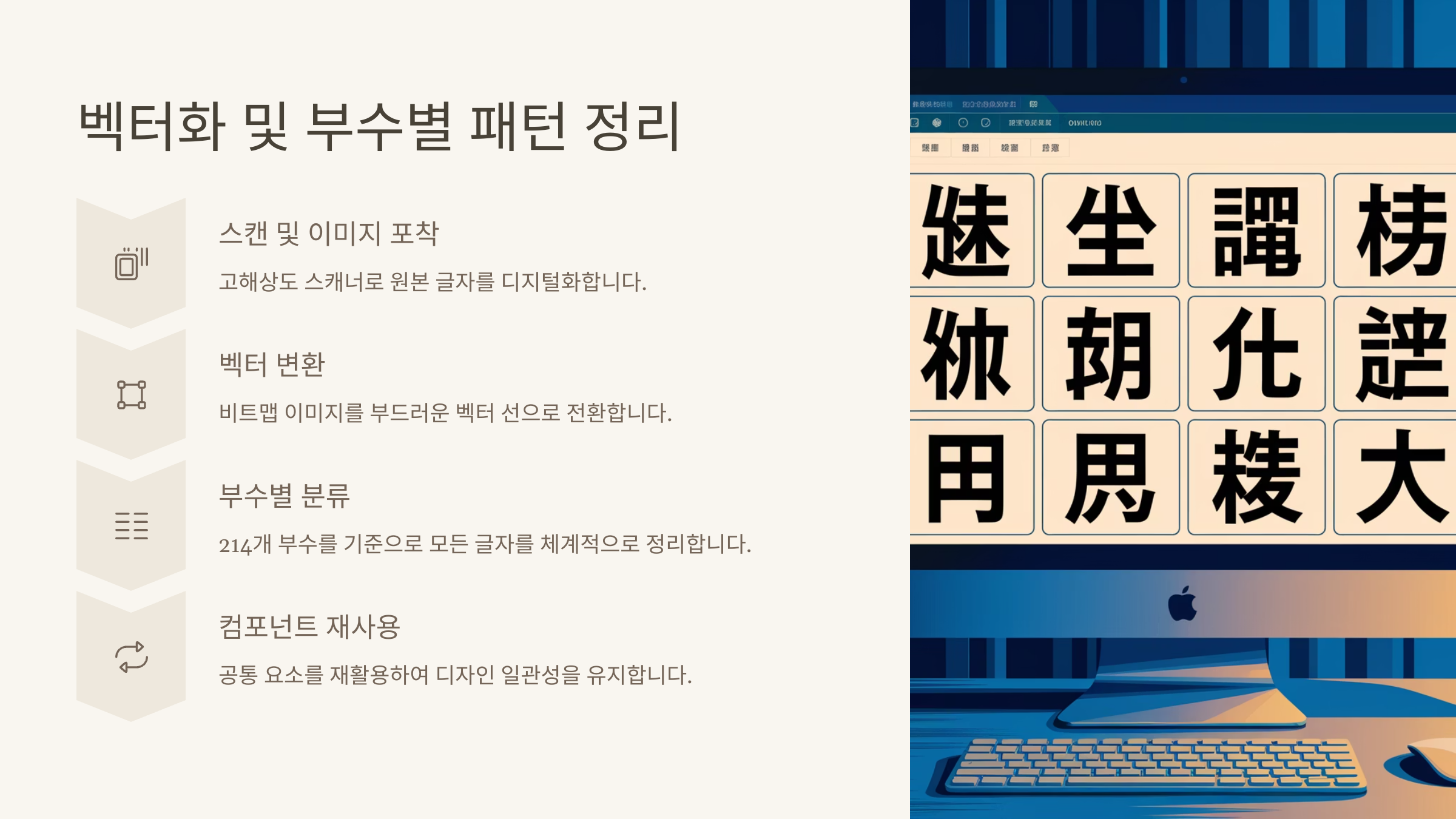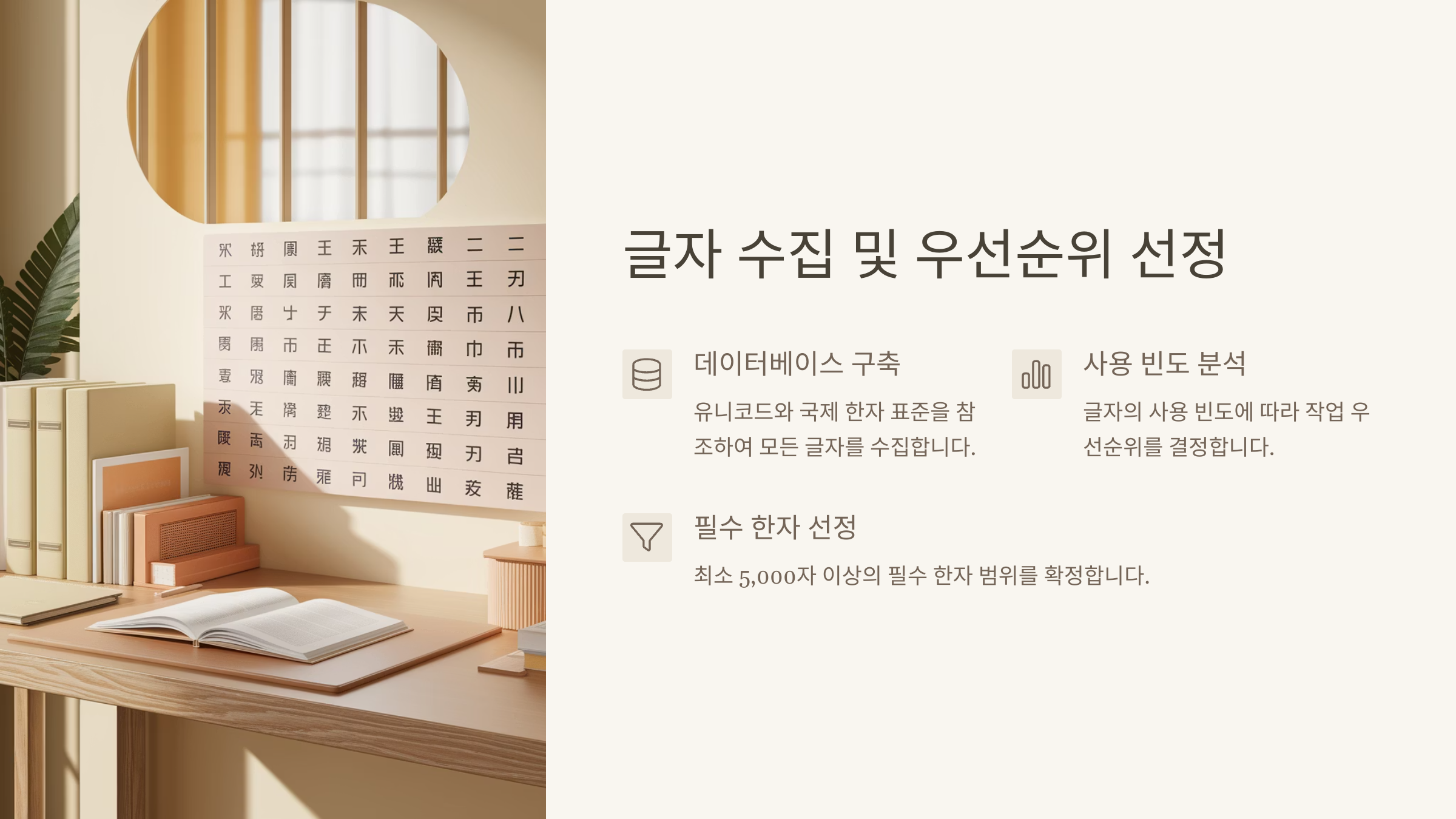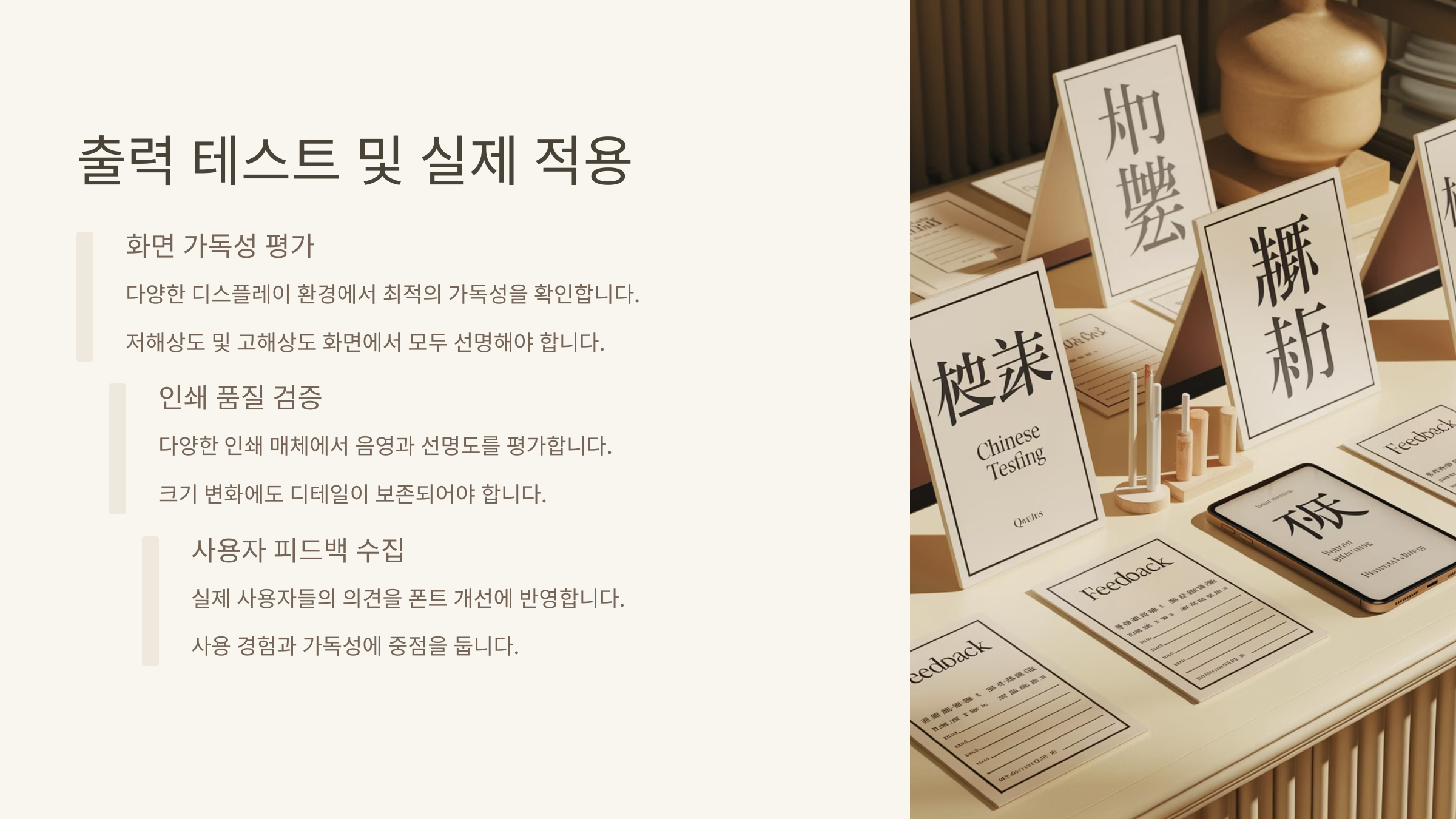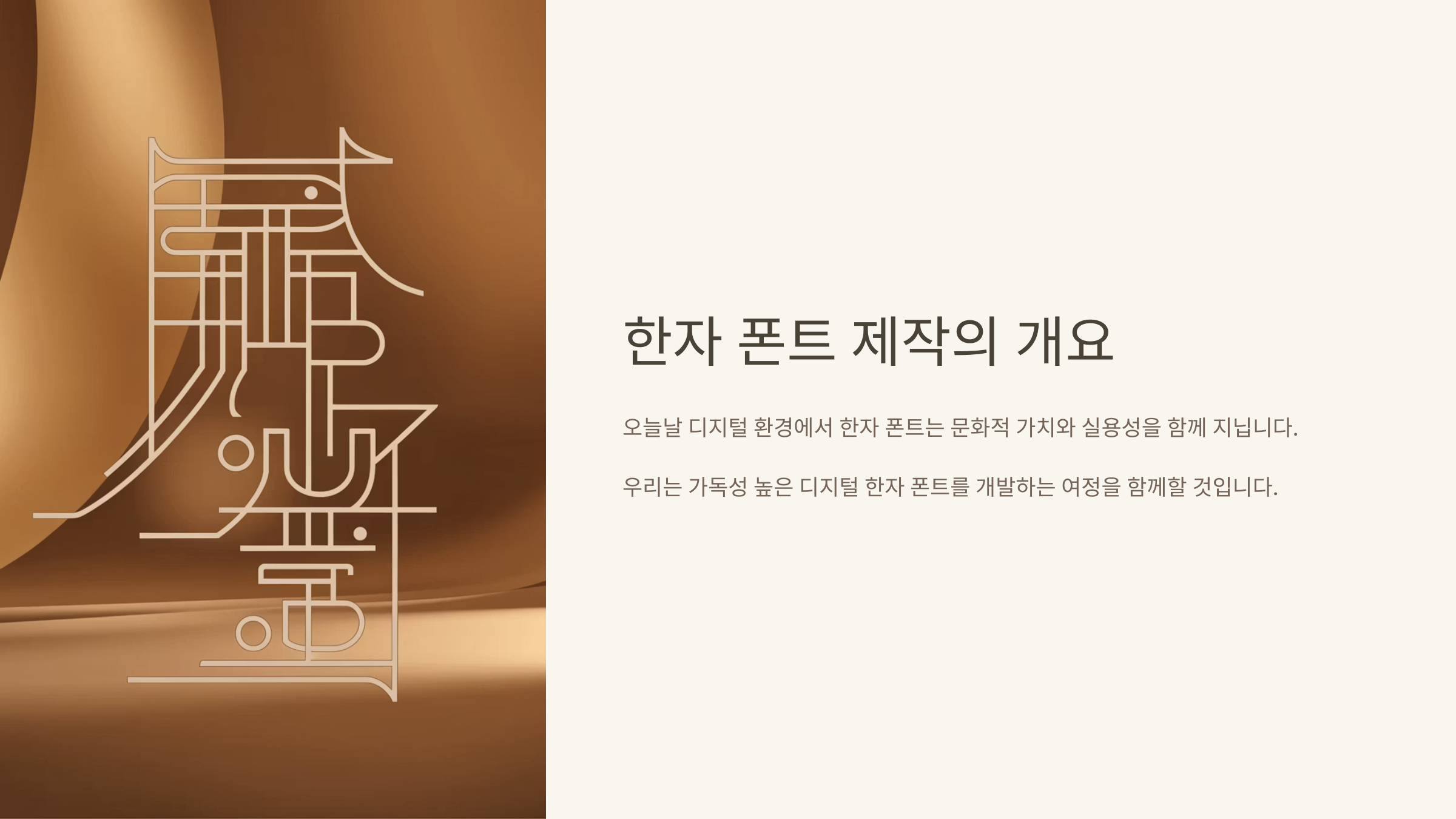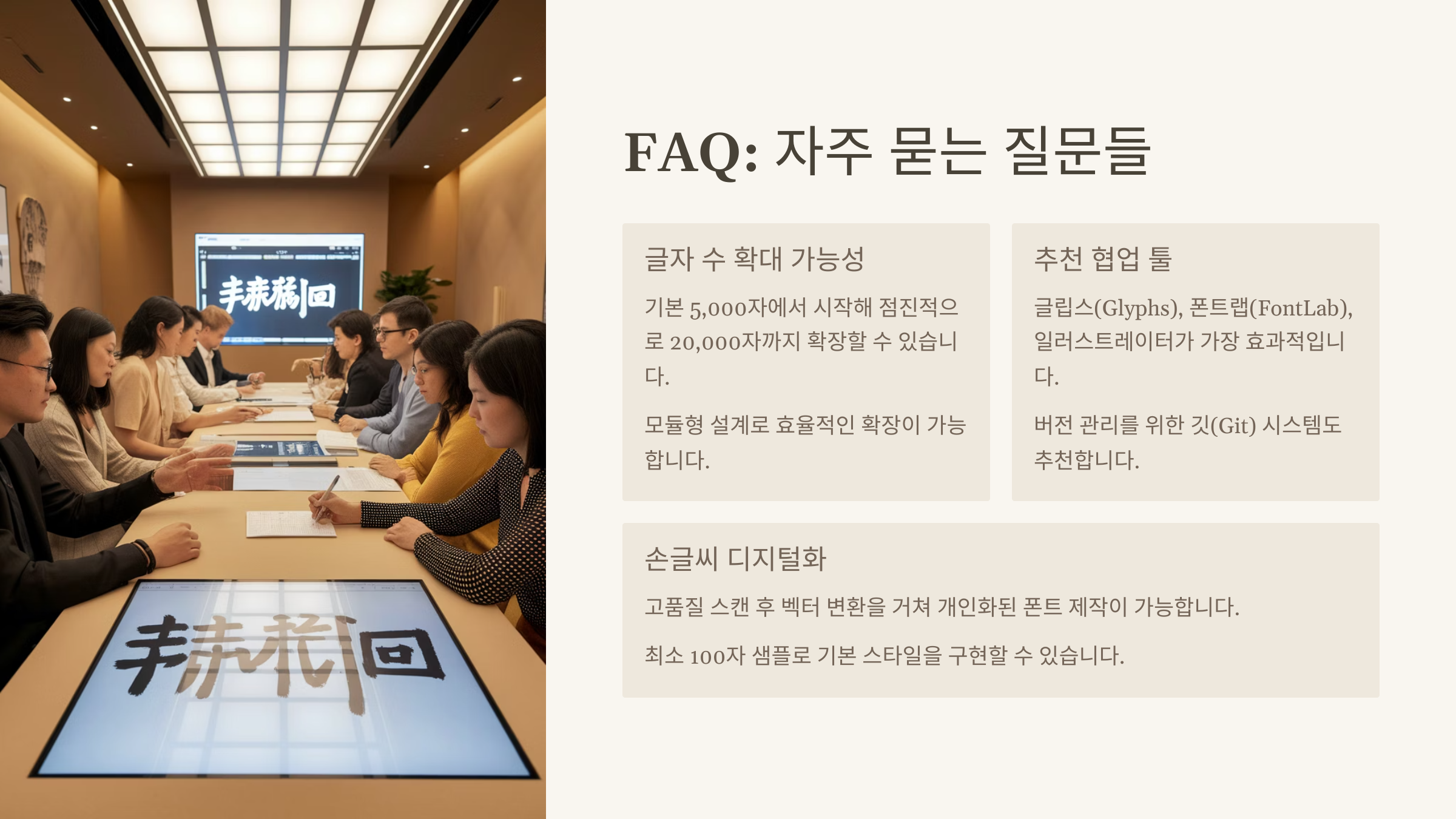
한자 폰트 제작은 일반 한글이나 영문 폰트보다 훨씬 복잡하고 방대한 작업이에요. 왜냐하면 한자는 수천 개의 글자를 포함하고 있고, 각 글자의 구조도 다양하기 때문이에요. 그만큼 완성했을 때의 성취감도 크답니다! 🀄
한자 폰트는 전통적인 서예에서 영감을 받은 디자인부터 현대적인 모노라인 스타일까지 다양하게 활용돼요. 특히 전통 행사나 동양적인 콘텐츠 디자인에서는 독창적인 한자 폰트가 큰 차별화 요소가 되기도 하죠.
지금부터는 한자 폰트를 직접 만드는 데 필요한 준비 과정부터 드로잉, 벡터화, 자동 조합, 테스트까지 모든 절차를 하나하나 소개해줄게요. 시작해볼까요? 😊
📘 한자 폰트 제작의 개요와 특징
한자 폰트는 기존의 알파벳이나 한글 폰트보다 훨씬 많은 글립을 요구해요. 기본적으로 중국어 간체자는 3,500자 이상, 번체자는 5,000자 이상이 필요하죠. 한국에서 사용되는 한자는 교육용 1,800자 외에도 인명, 고사성어 등에서 4,000자 이상이 쓰여요.
한자의 가장 큰 특징은 부수(部首)와 획의 조합이에요. 그래서 글자 전체를 하나씩 새로 그리기보단, 부수와 주요 구성 요소를 재활용할 수 있는 구조를 설계하는 게 핵심이에요. 이 부분이 자동화 가능한 구조 설계와 직결돼요.
한자 폰트를 만들기 위해서는 먼저 내가 만들고자 하는 범위를 정하는 게 중요해요. 전체 8천 자를 다 만드는 건 비현실적일 수 있으니, 1차로 300자, 2차로 1,000자 이런 식으로 범위를 나누는 게 효율적이에요.
또한 폰트의 용도도 정해야 해요. 웹용인지, 인쇄용인지, 로고 타입인지에 따라 선의 굵기나 정밀도가 달라져야 하거든요. 서예 느낌의 획감을 살릴지, 미니멀한 디지털 느낌으로 갈지도 처음부터 명확히 정해야 효율적인 제작이 가능해요. 🖌️
🈶 한자 폰트와 한글/영문 폰트 비교
항목 한자 폰트 한글/영문 폰트
필요 글자 수 3,000~10,000자 한글 2,350자 / 영문 100자
글자 구성 부수 + 파생부 + 결합 기본자 직접 제작
제작 방식 자동 조합 활용 필수 글립별 수동 제작 가능
내가 생각했을 때, 한자 폰트는 양적인 도전뿐만 아니라 구조적인 설계의 예술이에요. 드로잉 감각과 함께 데이터적 사고까지 요구되기 때문에 폰트를 진지하게 만들어보고 싶은 사람에게는 최고의 프로젝트라고 느껴져요. 🤓
📚 글자 수집과 우선순위 선정
한자 폰트 제작에서 가장 먼저 해야 할 일은 어떤 글자를 만들 것인지 정리하는 작업이에요. 한자 수는 무려 7만 자 이상이지만, 실생활에서 자주 쓰이는 글자는 그중 일부에 불과하거든요. 그래서 우선순위를 똑똑하게 정리하는 게 효율을 크게 높여줘요. 🧠
가장 기본이 되는 건 교육용 상용한자(1,800자)예요. 한국 교육과정에서 배울 수 있는 글자들이고, 일상적인 문서나 책에서도 가장 많이 쓰이는 글자들이에요. 국립국어원이나 한자능력시험 공식 웹사이트에서 리스트를 쉽게 찾을 수 있어요.
다음으로는 성씨와 이름에 자주 쓰이는 인명용 한자(약 5,000자)가 있어요. 디자인 명함, 족보, 졸업증명서 등 다양한 인쇄물에 활용되기 때문에 상용한자 다음으로 높은 우선순위예요. 이름에 자주 등장하는 글자는 폰트 가독성에서 특히 중요하답니다.
그리고 나서 고려할 수 있는 건 고사성어나 문장 구성에 자주 쓰이는 고빈도자(사용빈도 1,000위 이내 한자)예요. 뉴스, 논문, 고전 텍스트 등에서 반복적으로 등장하는 글자들을 데이터 기반으로 정리한 자료들도 있으니 참고하면 좋아요.
📖 한자 제작 우선순위 예시 리스트
우선순위 구성 추천 수량
1단계 상용한자 (교육용) 1,800자
2단계 인명용 한자 약 5,000자
3단계 고빈도/문장형 한자 약 500~2,000자
이렇게 정리된 우선순위에 따라 글자 목록을 엑셀이나 구글 스프레드시트로 관리해보면 좋아요. 어떤 글자가 완성됐는지, 어떤 글자는 부수가 겹치는지 추적할 수 있어서 제작 속도도 빨라지고 중복 작업도 줄어들어요. 📊
✍️ 한자의 구조와 드로잉 전략
한자는 하나의 글자가 곧 ‘작품’이에요. 단순한 획 몇 개로 이루어진 게 아니라, 부수와 파생부의 조합으로 복잡한 구조를 이뤄요. 그래서 드로잉을 할 때 가장 먼저 해야 할 일은 구성 분석이에요. 어떤 부분이 반복되고, 어디가 독립적인지를 파악하는 게 핵심이에요. 🔍
예를 들어, ‘語(말씀 어)’는 왼쪽에 言(말씀 언), 오른쪽에 吾(나 오)가 있어요. 이렇게 부수와 부수가 결합된 형태는 전체 드로잉을 다시 그리는 것보다 부분을 나눠서 조립하는 전략이 훨씬 효율적이에요.
그래서 보통 폰트 디자이너들은 자주 쓰이는 부수나 부속 요소를 따로 벡터로 만들어 두고, 이를 재조합해서 글자를 구성해요. 이렇게 하면 3천 자 이상을 만들 때 중복 작업을 줄일 수 있고, 스타일 일관성도 유지할 수 있어요.
획 순서와 균형도 중요해요. 한자는 획이 많기 때문에 전체 비율이 흐트러지기 쉬운데, 중심축과 획의 리듬을 고려해서 균형을 맞추는 게 핵심이에요. 너무 촘촘하게 그리면 인쇄나 웹에서 가독성이 떨어지고, 너무 벌어지면 품격이 떨어져 보여요. 🎨
🧩 한자 구성 요소 분석 예시
글자 좌우/상하 구성 부수 드로잉 팁
語 좌우형 言 言과 吾를 따로 제작 후 결합
學 상하형 子 ‘子’는 반복 사용, ‘冖’도 재활용
體 좌우형 骨 骨, 豆 등 부분별 드로잉 추천
한자의 드로잉은 시간이 오래 걸리지만, 부분을 잘게 쪼개서 모듈처럼 구성하면 효율이 엄청 올라가요. 게다가 나중에 다른 글자 제작에도 그대로 재활용 가능해서 작업 시간이 확 줄어요. 💡
🖱️ 벡터화 및 부수별 패턴 정리
드로잉이 끝났다면, 다음은 한자를 ‘벡터’ 형태로 정리하는 단계예요. 폰트 제작 도구에서 글립을 만들기 위해서는 모든 글자가 벡터 방식이어야 하거든요. 픽셀로 구성된 이미지는 확대하면 깨지지만, 벡터는 어떤 크기에서도 선명하게 유지돼요. ✨
일러스트레이터나 Glyphs, FontLab 같은 툴에서 펜 툴을 활용해 하나하나 선을 따주는 게 기본이에요. 이 작업은 처음엔 시간이 오래 걸리지만, 부수 단위로 만들어놓으면 반복해서 쓸 수 있어서 전체 글자 수가 많아질수록 효율이 급상승해요. 📈
이때 가장 중요한 게 ‘부수 패턴화*예요. 예를 들어 ‘氵(물 수)’ 부수는 여러 한자에서 같은 위치에 쓰이기 때문에 위치, 비율, 선의 곡률까지 동일하게 만들어야 전체 폰트에 통일성이 생겨요. 이런 부수별 템플릿을 만드는 걸 추천해요.
패턴화된 부수는 별도 레이어로 저장하거나, 라이브러리로 만들어 두면 이후 글립 조립할 때 쉽게 가져다 쓸 수 있어요. 특히 반복 부수(言, 木, 扌, 忄 등)는 반드시 템플릿화해서 재사용을 염두에 둬야 해요. 😎
🧱 대표 부수 패턴 정리 예시
부수 자주 사용되는 예 위치 벡터화 팁
氵 海, 洋, 湖 좌측 균형 맞춘 3획 반복 사용
言 語, 話, 記 좌측 글자폭 25% 내외로 고정
忄 情, 忍, 息 좌측 중앙축 기준 좌정렬
부수마다 고유 스타일을 정해두면, 새 글자 만들 때 고민할 게 확 줄어요. 처음에는 귀찮아 보여도, 부수 패턴화를 해두면 나중에 한자 1,000자를 만드는 데 드는 시간이 절반 이하로 줄 수 있어요. 효율의 핵심 포인트예요! 🚀
🔧 글립 조합과 자동 생성 기법
한자 폰트는 기본적으로 수천 개의 글립이 필요하기 때문에, 모든 글자를 수작업으로 만드는 건 사실상 불가능해요. 그래서 조합 시스템과 자동 생성 기법을 활용하는 게 핵심이에요. 🧠
먼저, 글립 조합은 앞에서 벡터화한 부수들과 파생 구성 요소를 레고처럼 조립해서 새로운 글자를 만드는 방식이에요. 예를 들어 ‘語’는 이미 만든 ‘言’ 부수와 ‘吾’ 요소를 불러와 적절한 위치에 배치하면 완성돼요. 이렇게 하면 반복 작업 없이 수많은 글자를 빠르게 만들 수 있죠.
더 나아가면 Python 스크립트나 Glyphs 앱의 스마트 컴포넌트 기능을 활용해 자동으로 글립을 생성할 수 있어요. 예를 들어 ‘氵+青=清’ 같은 규칙을 알고리즘으로 정해두면, 비슷한 조합의 글자들을 자동 배치해서 글립을 생성해주는 거예요. 💡
이런 자동화 방식은 특히 상업용 대규모 폰트를 제작할 때 필수예요. 기계적으로 반복되는 글자의 패턴을 파악해서 구조적으로 만들어놓으면, 유지보수도 쉬워지고 수정도 빠르게 반영할 수 있어요. 효율과 품질을 동시에 잡는 방식이에요!
⚙️ 자동 조합 방식 예시
조합 방식 예시 글자 구성 요소 활용 도구
좌우 조합 語 言 + 吾 Glyphs Smart Component
상하 조합 學 冖 + 子 + 冓 FontLab Scripts
복합 조합 體 亻 + 骨 + 豆 Python 자동 조립
자동화 도구는 배우는 데 시간이 조금 걸릴 수 있지만, 한자 폰트를 제대로 만들고 싶다면 정말 강력한 무기예요. 나만의 조합 규칙을 시스템화해두면, 이후 프로젝트에서도 계속 활용할 수 있어요. 진짜 실력자처럼 작업할 수 있는 비법이죠! 🚀
🧪 출력 테스트 및 실제 적용
글립을 조합하고 폰트 파일로 내보낸 뒤에는 반드시 출력 테스트를 거쳐야 해요. 한자는 획이 많고 복잡한 만큼, 화면과 인쇄에서 문제가 생기기 쉬워요. 그래서 최종 완성 단계에서 다양한 환경에서 꼼꼼하게 확인하는 게 정말 중요해요. 🧐
먼저, 화면 테스트를 해볼게요. 워드나 한글, 포토샵 같은 프로그램에서 한자 문장을 입력해보세요. “語言文字文化”, “漢字生成機能” 같이 구조가 다양한 문장을 활용하면 오류를 쉽게 발견할 수 있어요. 자간, 획의 간섭, 불필요한 겹침 등을 중점적으로 봐야 해요.
그다음은 인쇄 테스트예요. A4 크기에서 폰트를 8pt, 10pt, 14pt 등 다양한 크기로 인쇄해보면 글자의 가독성을 확인할 수 있어요. 이때 너무 얇은 획은 날아가거나, 너무 굵은 획은 번짐 현상이 생기기도 하니 균형이 중요해요.
웹 테스트도 빼놓을 수 없어요. 폰트를 `.woff`나 `.woff2`로 변환해서 `@font-face`로 불러온 후 웹페이지에 적용해보세요. 한자가 깨지지 않고 잘 로딩되는지, 모바일 반응형에서도 이상 없는지까지 꼭 확인해야 해요. 📲
A5. 필수는 아니지만, Python 등 기본적인 스크립트를 알면 수천 자 작업을 훨씬 수월하게 할 수 있어요. Glyphs는 GUI 기반 자동화도 지원해요.
Q6. 한자 폰트를 만들 때 부수 기준이 꼭 필요하나요?
A6. 네, 부수 기준으로 구조를 나누면 재사용성과 일관성이 높아져요. 특히 좌우/상하형 패턴화에 꼭 필요해요.
이제 한자 폰트를 만드는 데 필요한 전 과정과 전략, 실전 팁까지 완벽하게 배워봤어요! 🎉
복잡해 보이지만, 하나씩 쌓아가다 보면 어느새 1,000자 이상의 폰트를 만들고 있는 자신을 발견하게 될 거예요. 시작이 반, 그리고 구조화는 곧 속도예요!